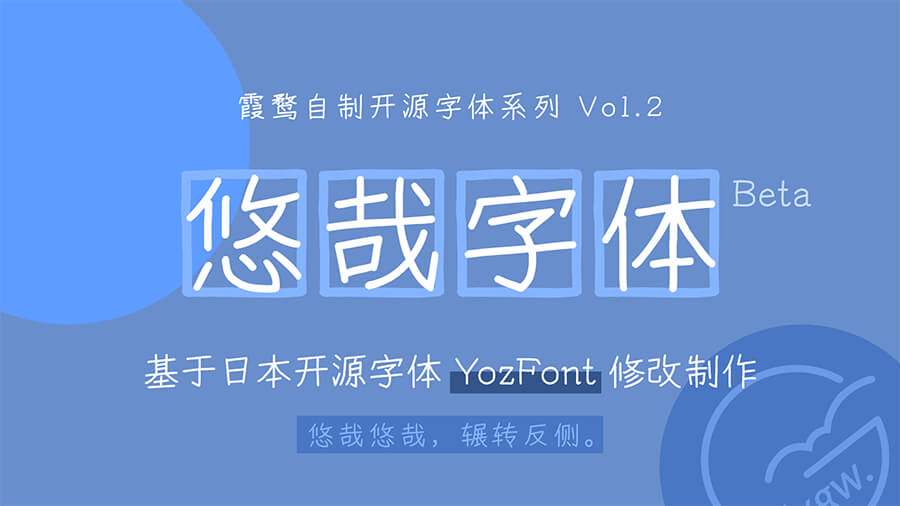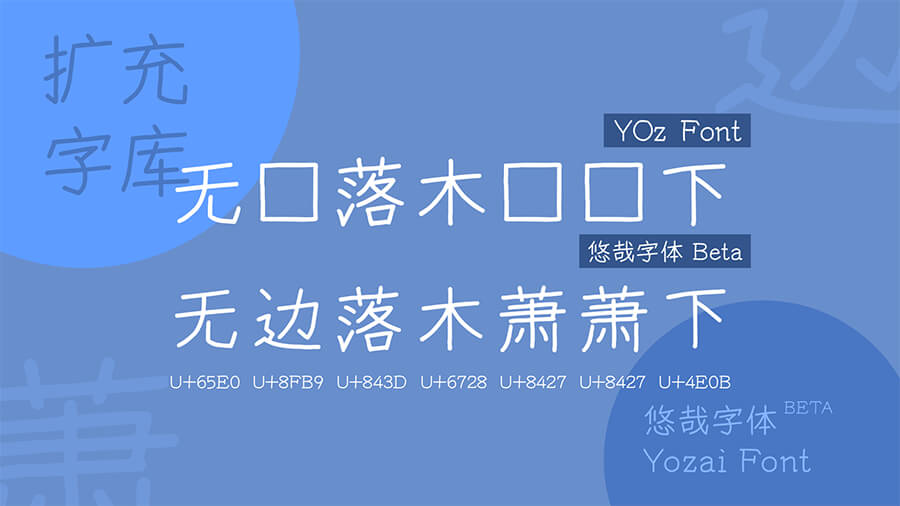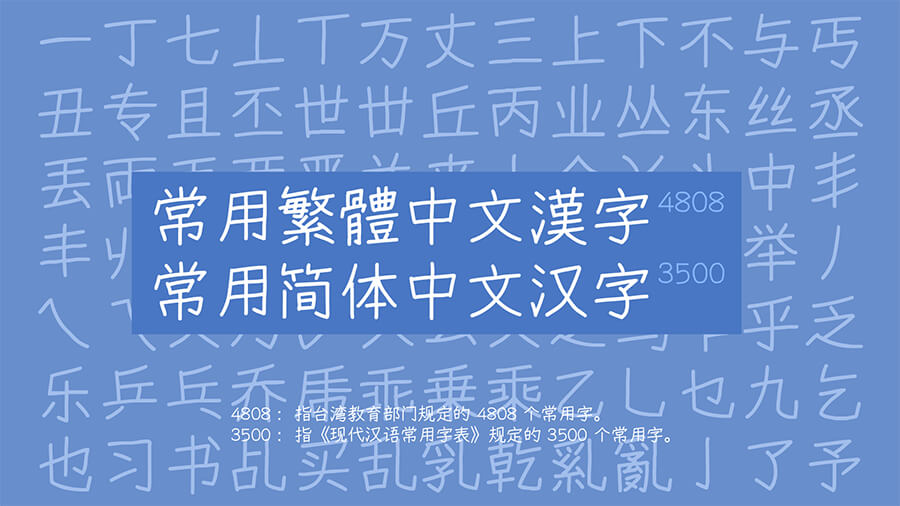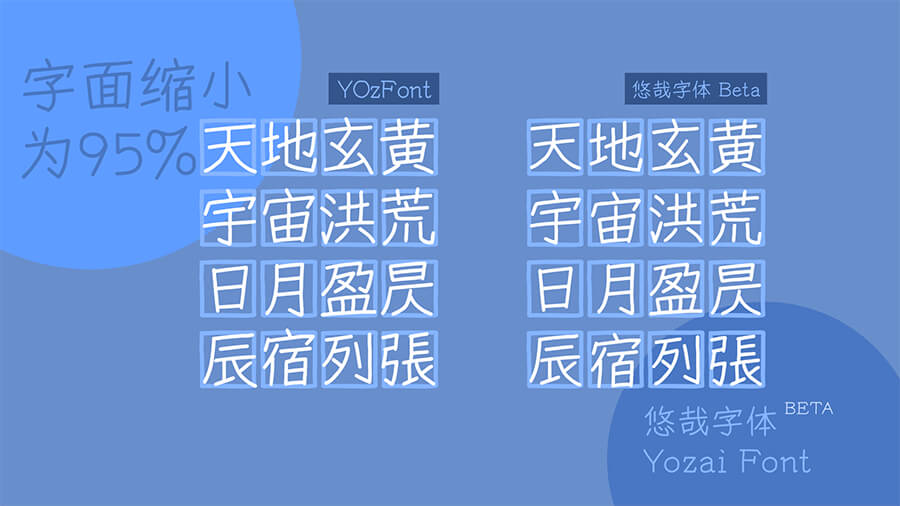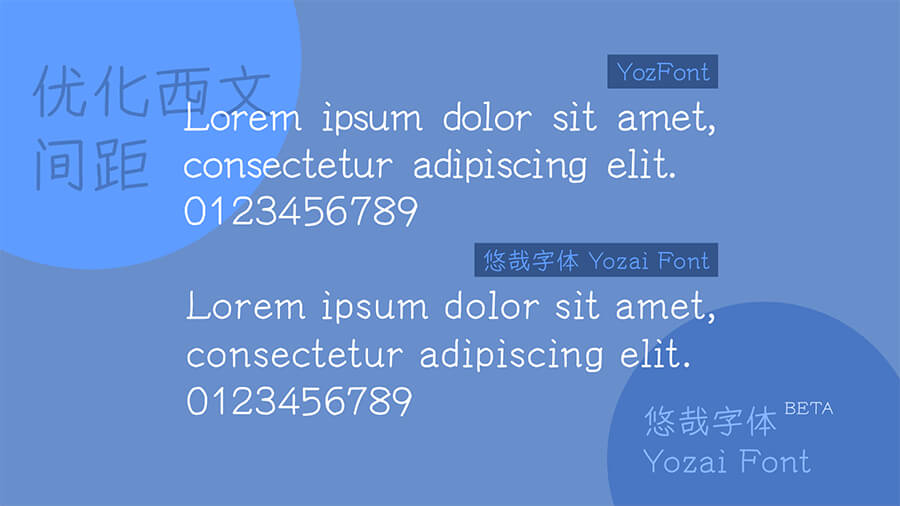
悠哉字体是一款基于Y.OzFont的手写风格的字体。目前已补全原字体中有对应繁体字的简体字,并补全了4808常用繁体中文汉字,以及3500常用简体中文汉字。4808 常用繁体中文汉字是指台湾教育部门规定的 4808 个常用汉字。3500常用简体中文汉字是指《现代汉语常用字表》规定的 3500 个常用汉字。
悠哉字体在原Y.OzFont的基础上,字面缩小至原来的 95%,并优化西文和标点符号的显示。
1. 本字体仍处于测试版,部分汉字还是处于日本写法,且字库并不是很全。 计划 补全 GB 2312 范围内的所有汉字,并更正 GB 2312 内汉字的写法为中国内地的字形。
2. 本人并不是专业的设计师,并未考虑设计美感,所以看起来可能略丑,补进去的字与原版可能略有违和感,但是聊胜于无。